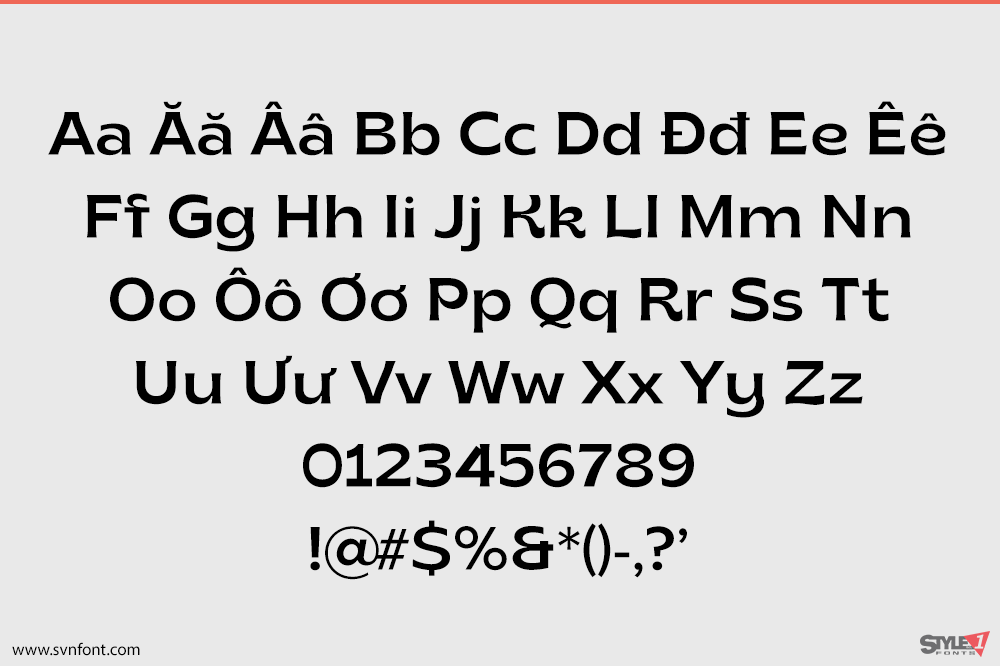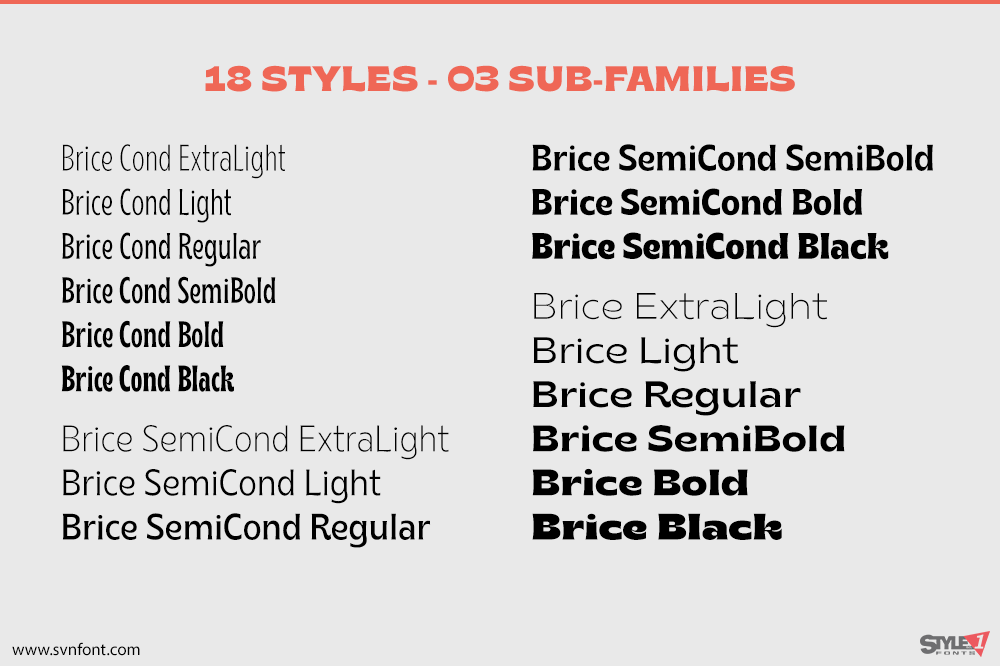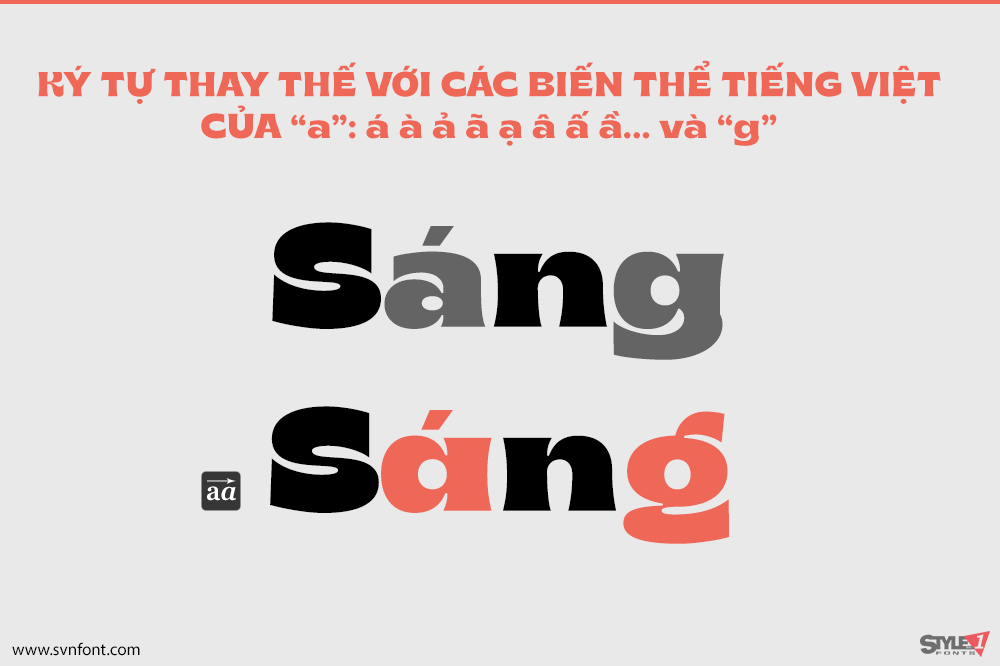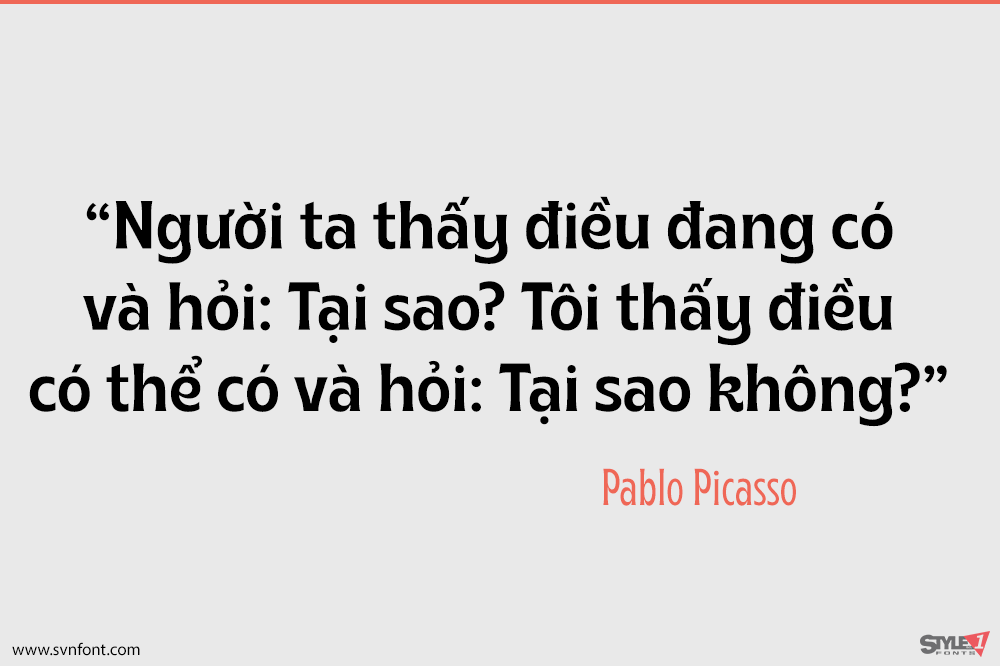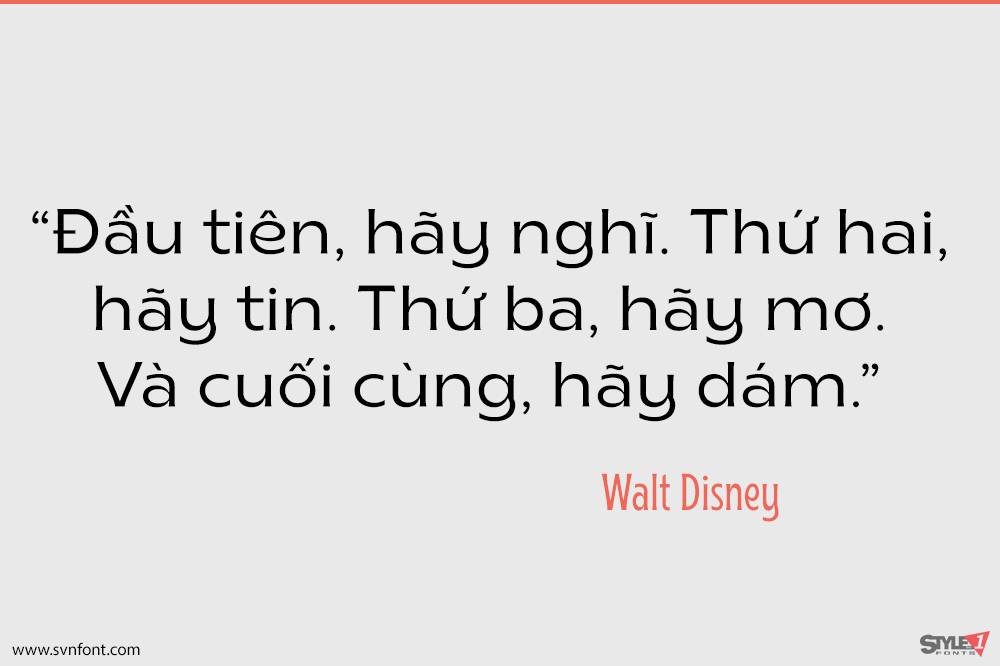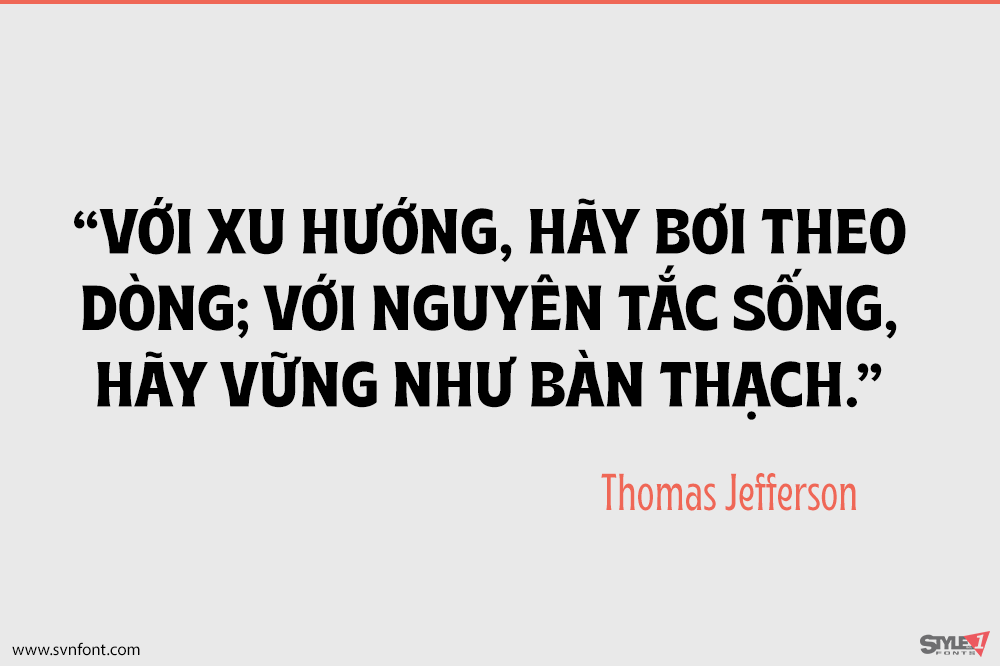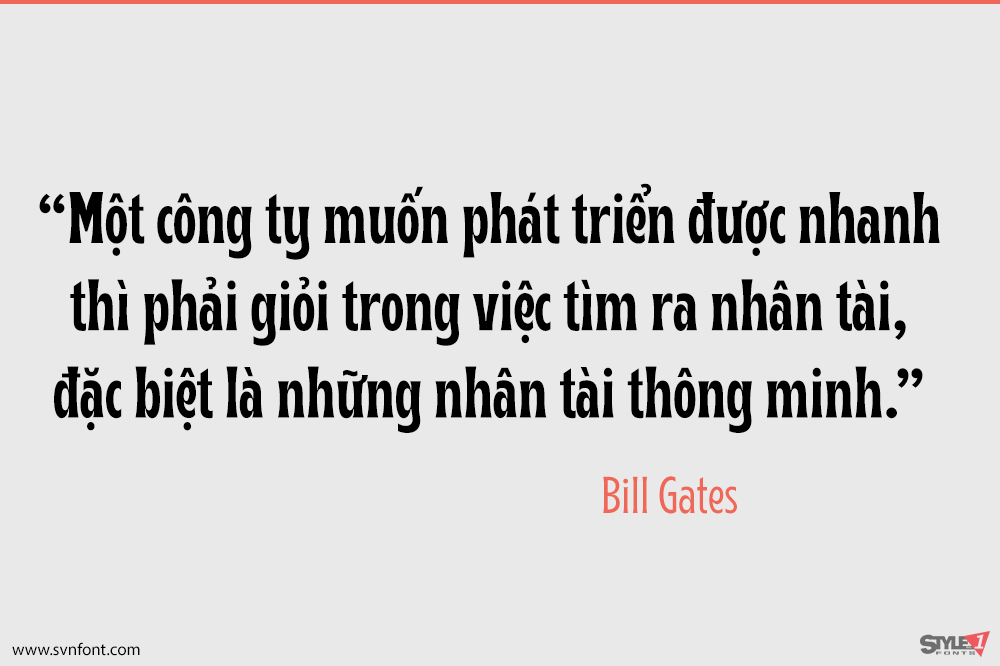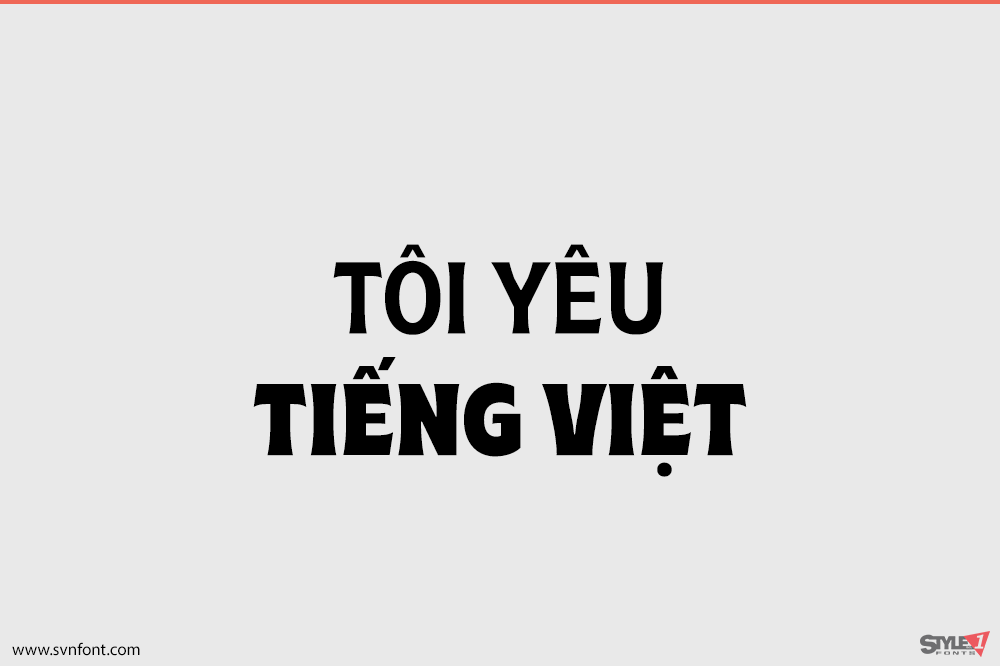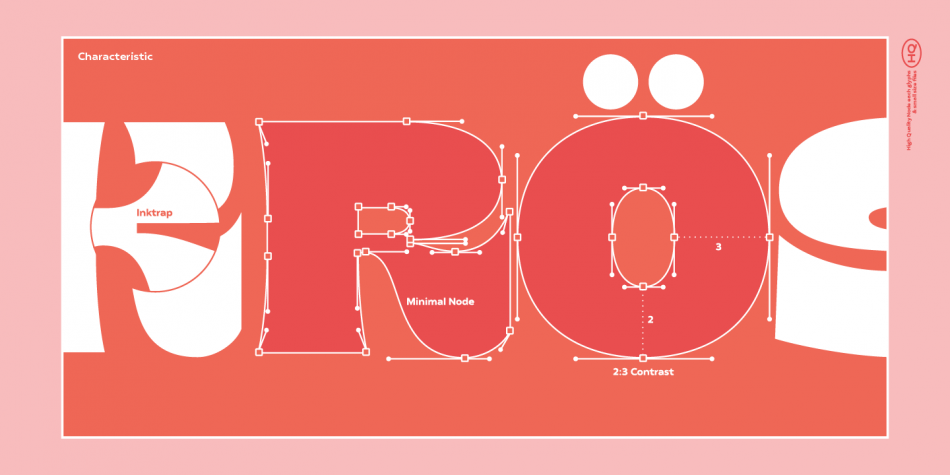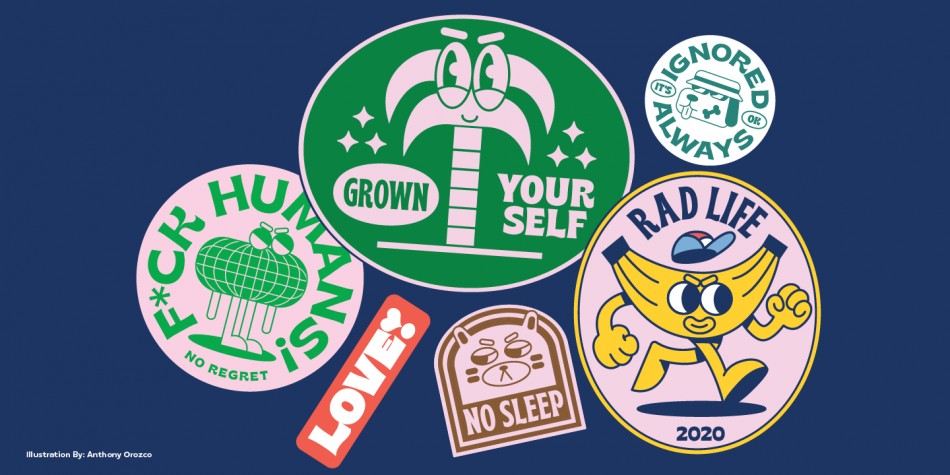
Brice đề cập đến các sản phẩm văn hóa của thập niên 80 như âm nhạc, nghệ thuật, văn học, thời trang, khiêu vũ và điện ảnh được tiêu thụ bởi phần lớn dân số. Đặc điểm của phông chữ Brice là các nét serif nhỏ, nảy và độ tương phản động, chẳng hạn như ở các chữ R, B, S, K, P, v.v. Nó hoàn hảo cho việc thiết kế logo, chú thích và tiêu đề. Phông chữ Brice có 5 độ rộng (Condensed – SemiCondensed – Normal – SemiExpanded – Expanded) với 6 độ đậm tương ứng (ExtraLight – Normal – SemiBold – Bold – Black) và hỗ trợ hơn 75 ngôn ngữ.